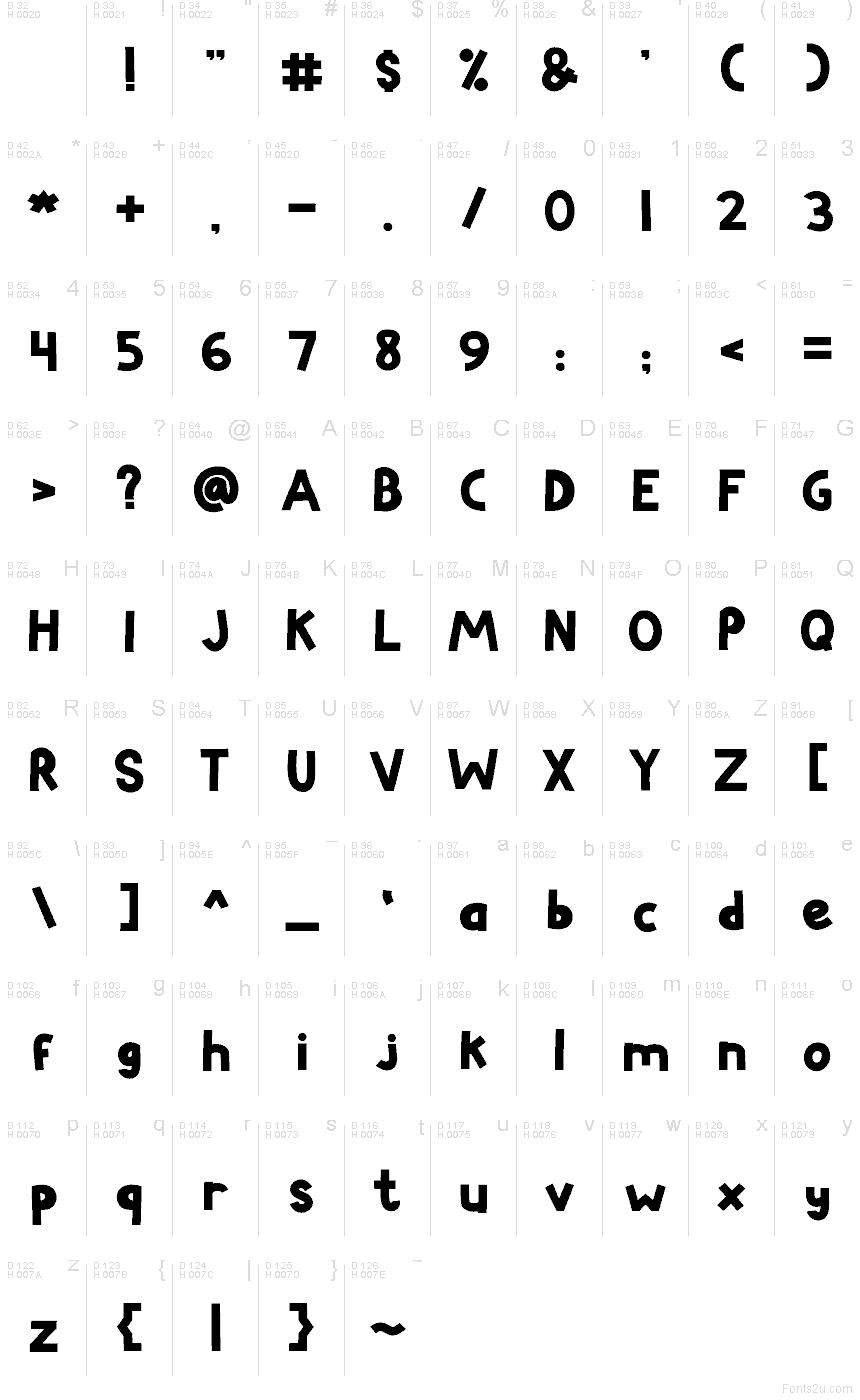
Lombardo
Lombardo od Tokokoo je bezplatné kreslené písmo, ktoré vyniká robustnou stavbou, jemnými hranami a hravým retro-popovým vzhľadom. Písmená sú výrazné, využívajú široké tvary a priateľské krivky, vďaka čomu abeceda nepôsobí stroho, ale naopak, veľmi živo a hravo.
Prirodzene sa hodí na obaly, branding pre deti, titulky plagátov, komiksové názvy a výraznú grafiku na sociálne siete, kde bezplatné písmo potrebuje okamžite vyžarovať teplo a mať výraznú siluetu. Zvlášť dobre funguje v krátkych heslách a logotypoch, pretože jeho hrubé, zaoblené tvary sa prirodzene spájajú do kompaktných a veselých textových blokov.